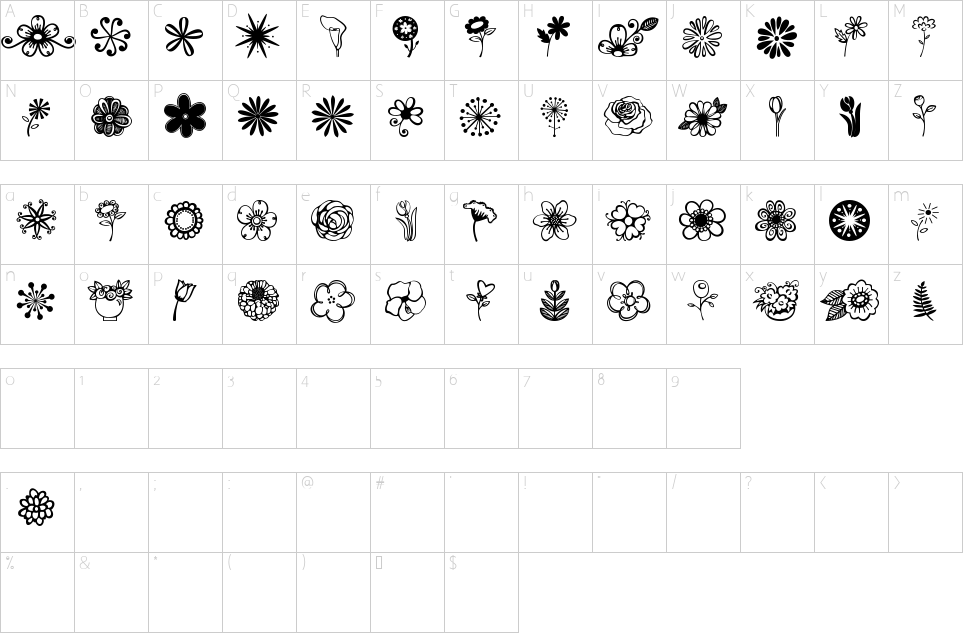
Descubra uma nova fonte gráfica, a Janda Flower Doodles, disponível para download gratuitamente. Criada por Kimberly Geswein, esta fonte é uma jóia entre as 1001 Free Fonts. Janda Flower Doodles oferece um visual suave e delicado, ideal para ambientes gráficos delicados, como design gráfico infantil ou editoriais de conteúdo pessoal. Seja você um designer de gráficos ou um editor de texto, essa fonte leva um toque de criatividade e suavidade à sua produção. Recentemente, a fonte foi baixada 31.037 vezes, mostrando sua popularidade e a qualidade inegável que ela oferece. Experimente ela agora e enriqueça seu trabalho com uma fonte singular e agradável aos olhos.